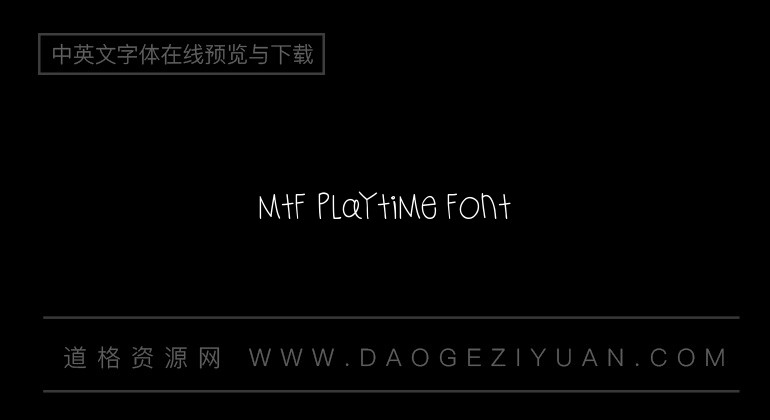
MTF Playtime Font
MTF Playtime Font 是一种可爱的手写风格字体,常见于儿童书籍、宣传海报、营销广告等设计中。该字体由一个名为“Miss Tiina”的设计师所创建,字母间距宽松,字母形状圆润有趣,整体呈现出轻快、活泼的感觉。 MTF Playtime Font 包含大写字母、小写字母、数字、标点符号等常用字符,同时还提供了一些额外的装饰性字符,例如小星星、心形等。这些装饰性字符可以帮助设计师制作出更具有趣味性和吸引力的设计作品。
MTF Playtime Font是一款非常不错的手写艺术字体,具有很好的视觉感,适合于文化类的宣传设计、商业类品牌的广告和产品包装设计以及个性化文字排版等较多场景。